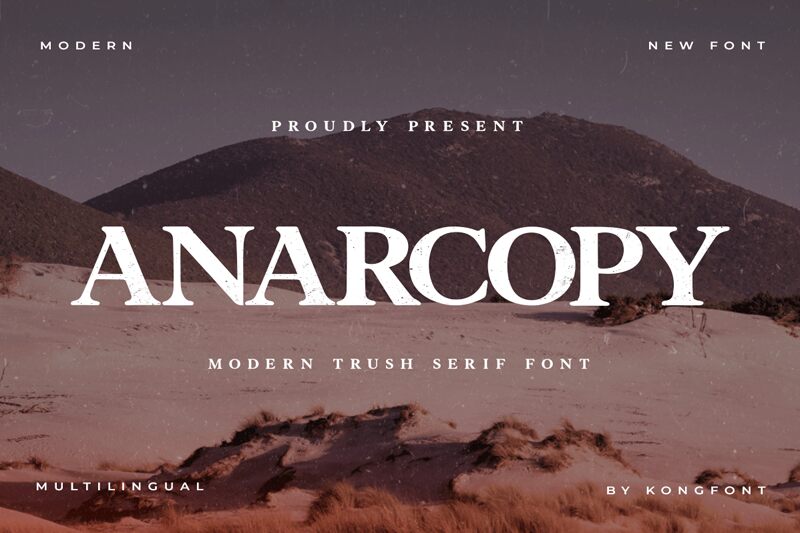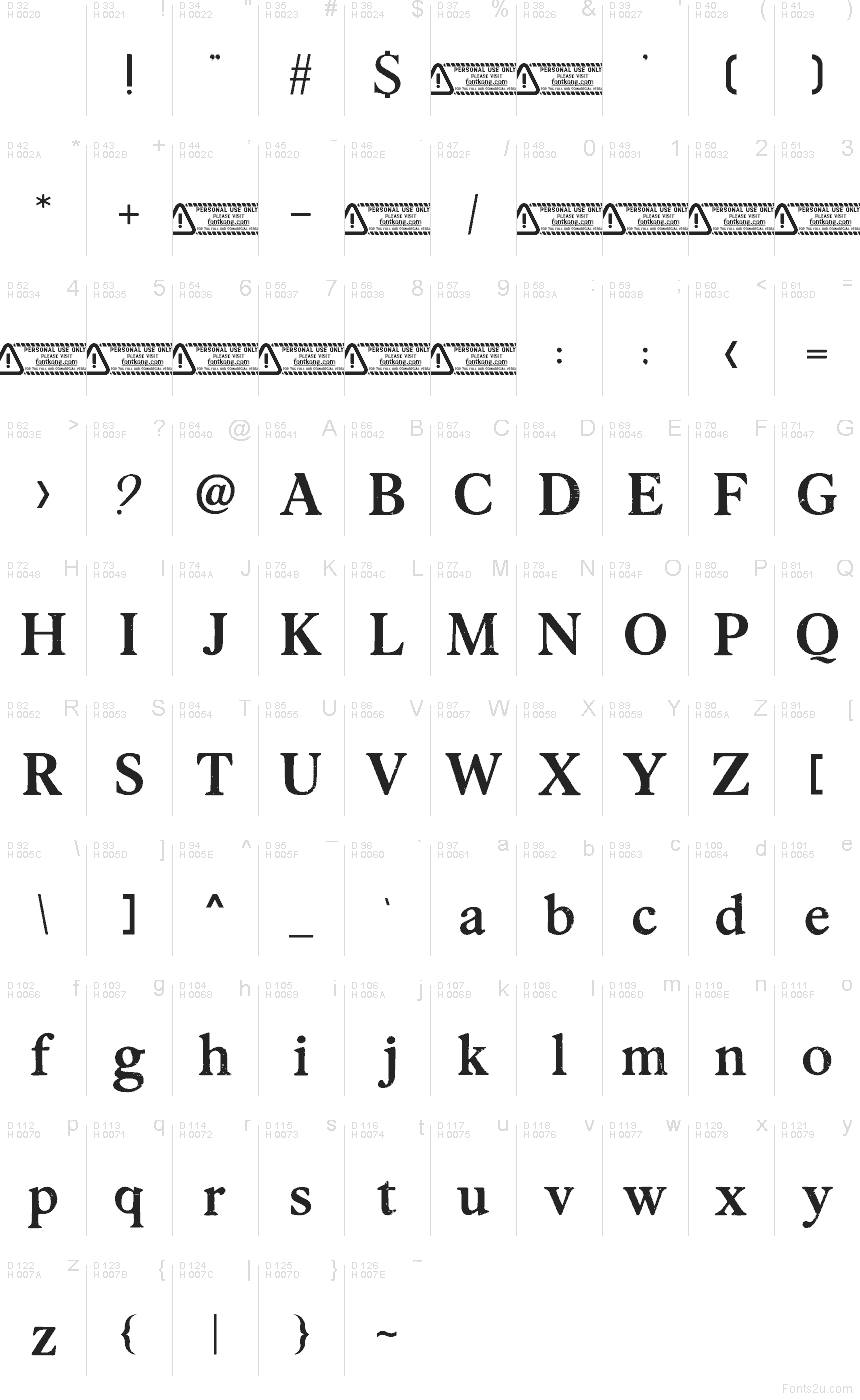
Anarcopy von Kong Font ist eine kostenlose, distressed Serifenschrift mit einem leicht literarischen Old-Style-Charakter. Die Buchstaben kombinieren vertraute, buchähnliche Formen mit rauen Sprenkeln und abgeplatzten Kanten. Dadurch wirkt die Schrift eher eingetragen als formell, während die abgerundeten Serifen verhindern, dass die verwitterte Textur zu hart wirkt.
Sie ist überall dort ideal, wo Überschriften Charakter und Grit brauchen, ohne dabei ins rein Dekorative abzugleiten – etwa bei Plakatüberschriften, Zine-Covern, Indie-Verpackungen, redaktionellen Aufmachern oder stimmungsvollem Branding. Als kostenlose Schrift funktioniert Anarcopy am besten in kurzen Zeilen, Zitaten oder Titelkarten, wo die brüchige Textur und der weiche Rhythmus der Serifen für sich sprechen können.